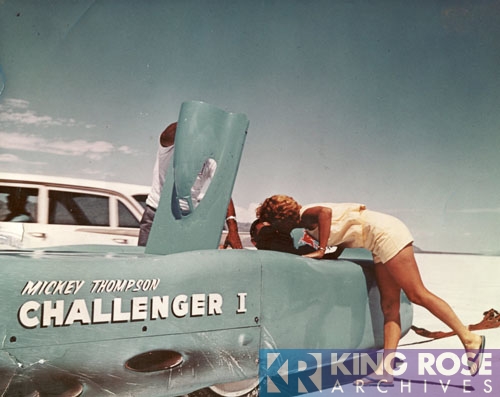
Suche Schrift aus Foto
ich suche die entsprechenden Schriftarten ("Mickey Thompson", "Challenger I") hier aus dem Foto, welche auf dem Auto abgebildet sind. Leider kann ich das mit Whatthefont nicht bestimmen.
Um diese Zeit war ein erfahrener Schildermaler am Werk, der wird sich von Displayschriften inspirieren lassen, aber keine vorhandene 1:1 auf das Fahrzeug umgesetzt haben.
Ähnlich für Mickey Thompson:
Calgary Script
Coffee Service